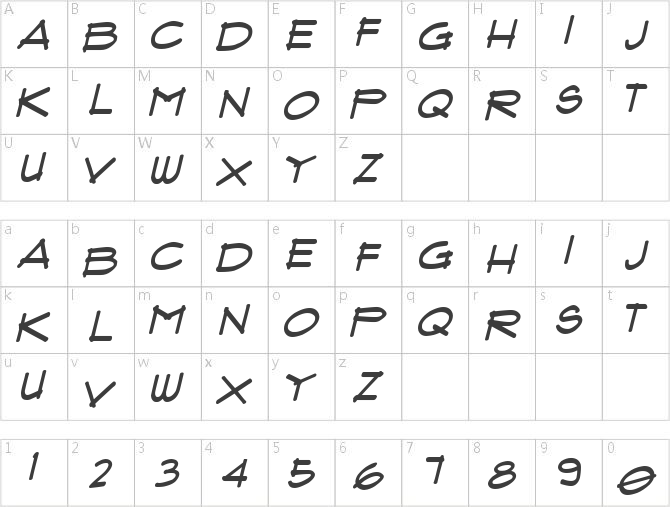
Flux Architect Italic
Flux Architect Italic介紹
Flux Architect Italic字體字庫是一款讓人賞心悅目、百看不厭的英文字體,適合各類廣告和產(chǎn)品包裝設計應用,字體大小0.02MB,格式為ttf字體,上傳用戶是sygyve520,作者/版權(quán)方為未知